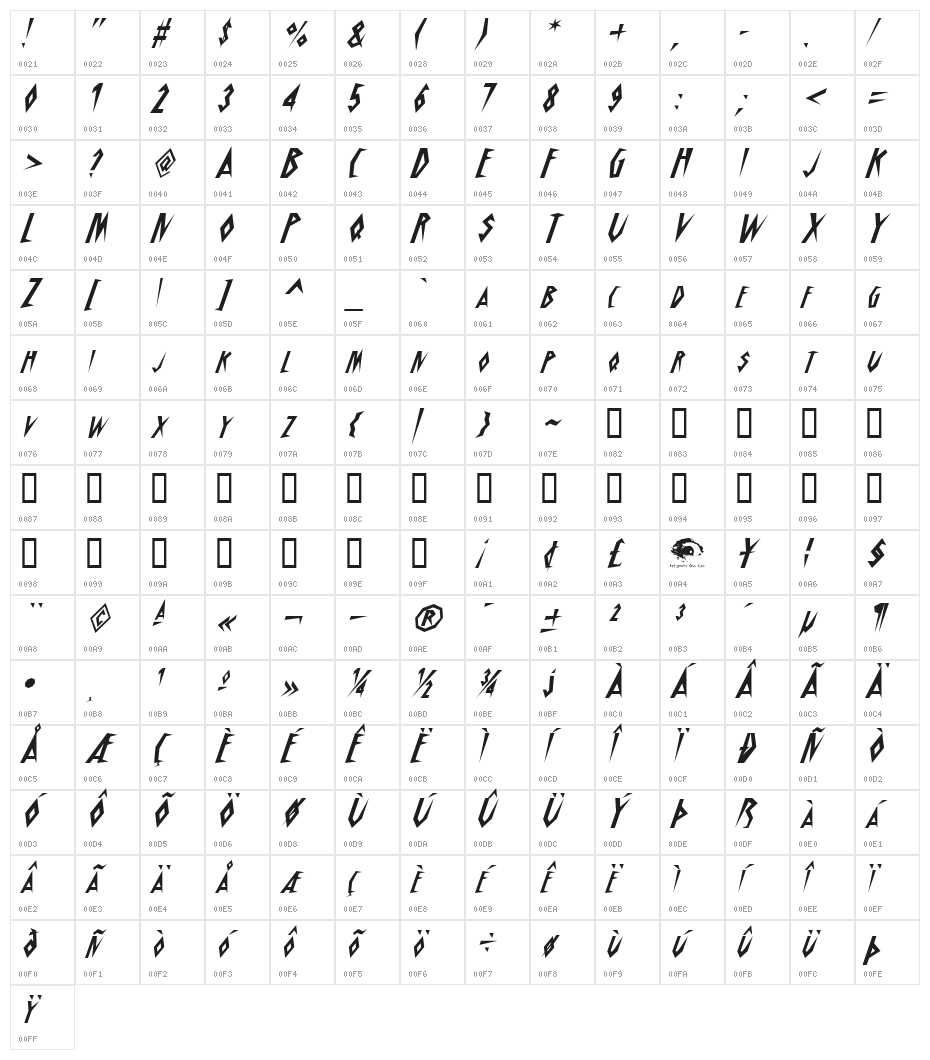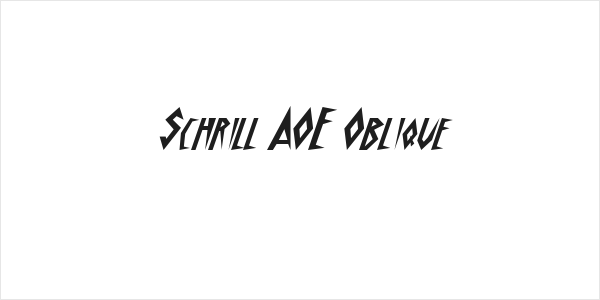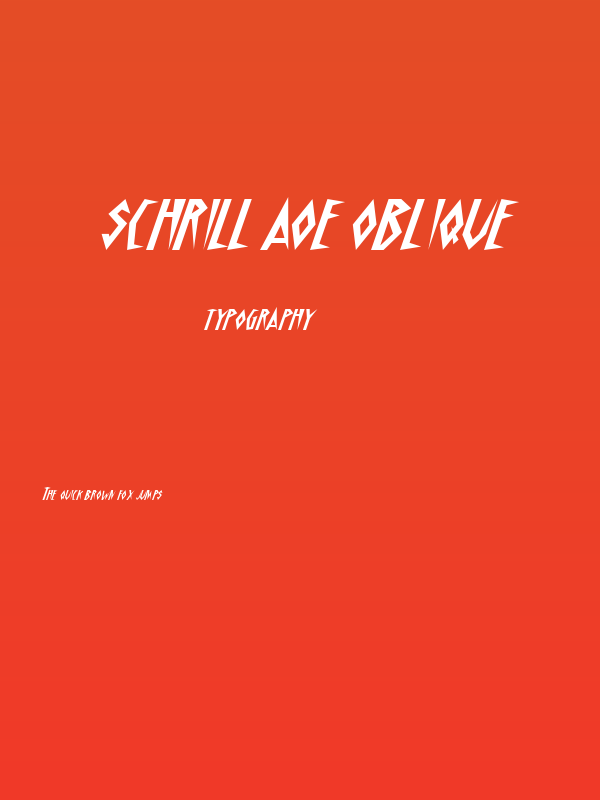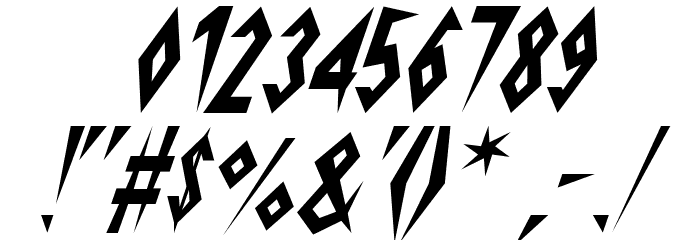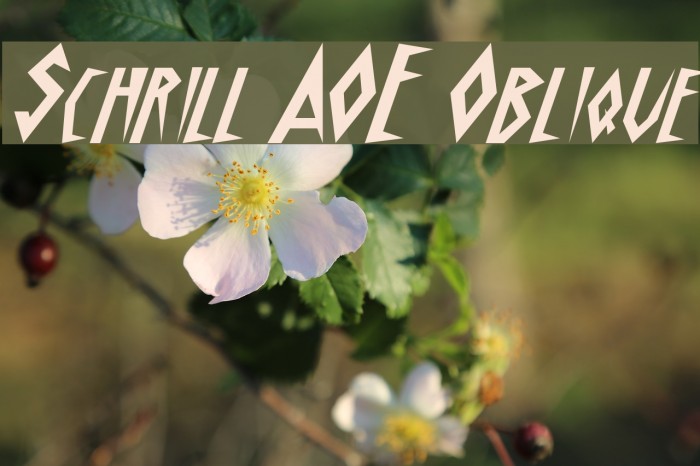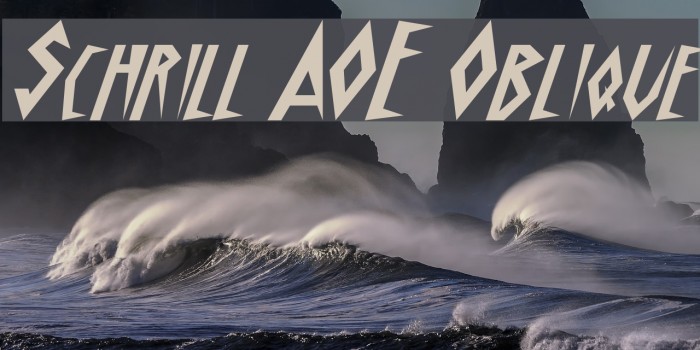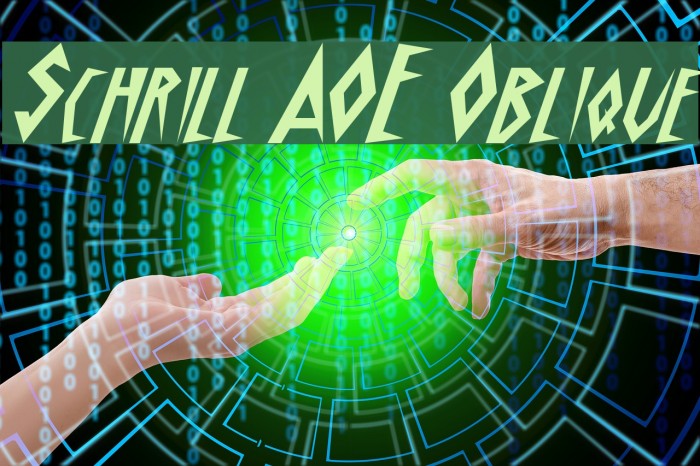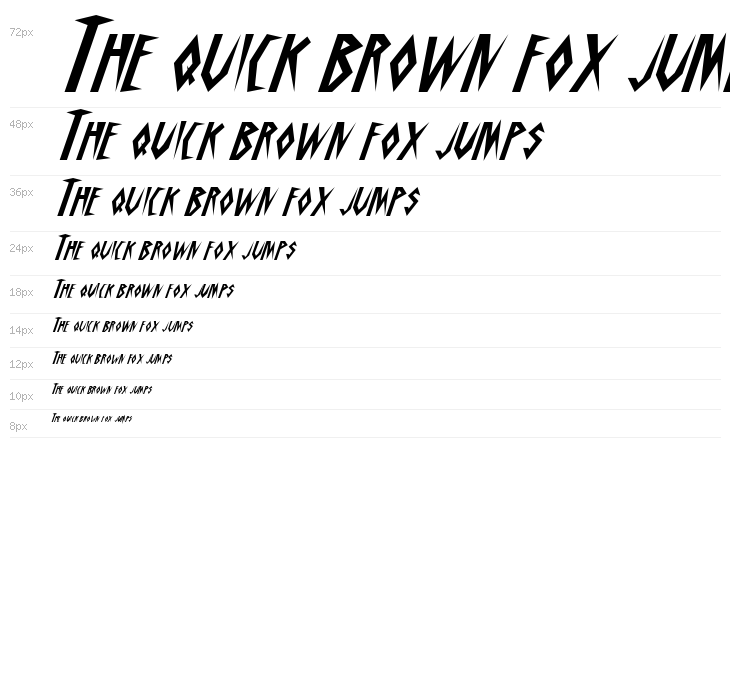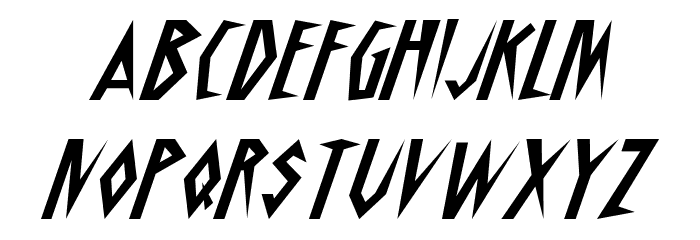
Schrill AOE Oblique Font
| Kategorien | Decorative |
| Gesamtstil | Modern, Energetic |
| Vorgeschlagene Projekte | Ideal for music album covers, sports team logos, action movie posters, and edgy branding materials. |